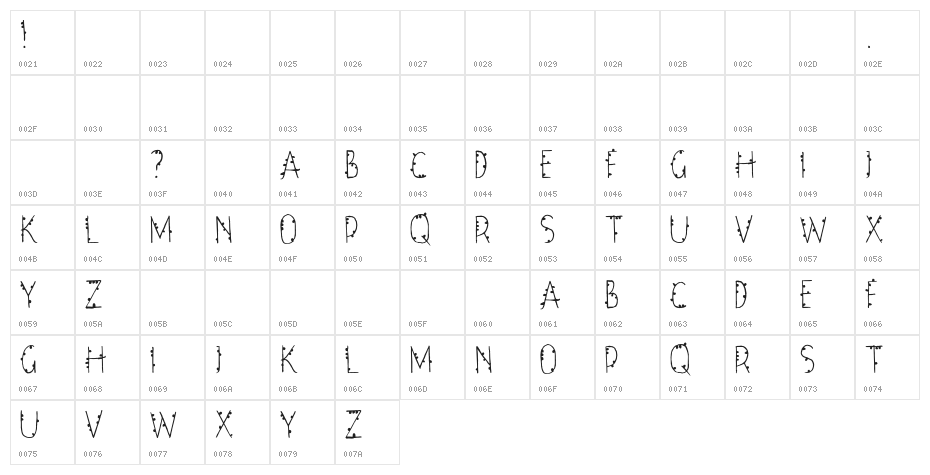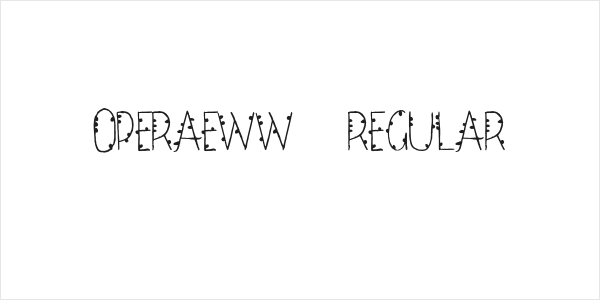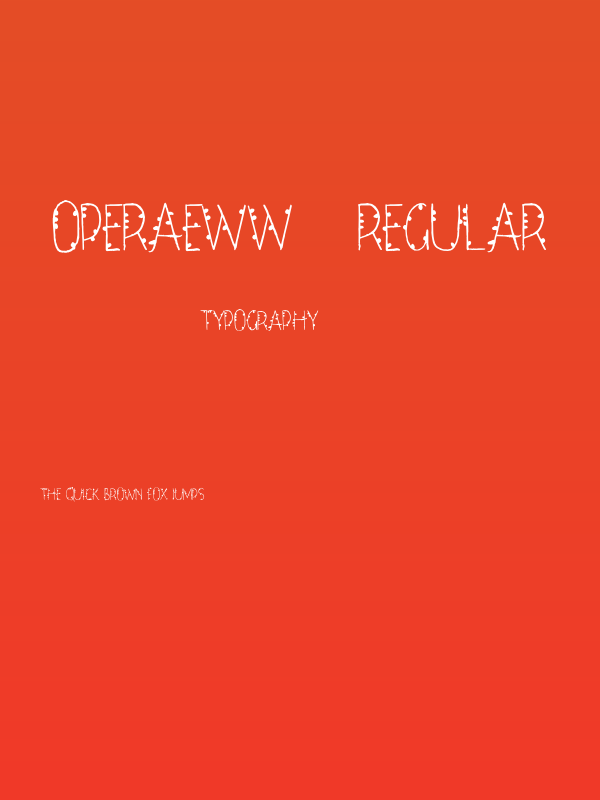
OperaEww-Regular Font
| Anwendungsfall | Headlines, Logos, Artistic projects |
| Vorgeschlagene Projekte | Ideal for artistic projects, invitations, posters, and branding that require a creative and unique touch. |